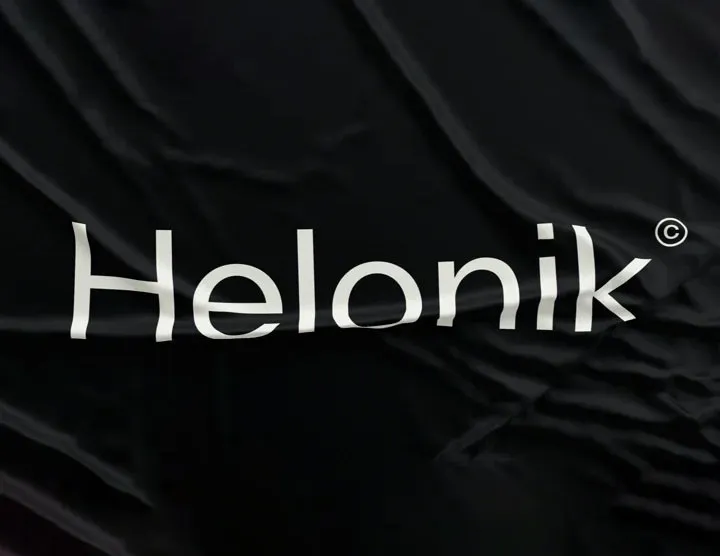
A Helonik Font é uma família de fuentes sans serif cuidadosamente concebida por Ckhans Fonts. Ela combina elementos minimalistas e limpos para atender às tendências atuais de design. A Helonik possui 22 tipos distintos, organizados em três tamanhos ópticos: Display. O tamanho mais grande é projetado para destacar a sutileza da fonte, ideal para headlines, enquanto os textos mais pequenos priorizam legibilidade com traços robustos e espaçamentos confortáveis. Inclui suporte para idiomas extensos, icones, fracionamento, linhas tabulares e ligaturas, garantindo que seja uma escolha versátil para projetos diversos. Compreender estas características pode permitir um uso mais flexível desta fonte no seu próximo projeto gráfico.